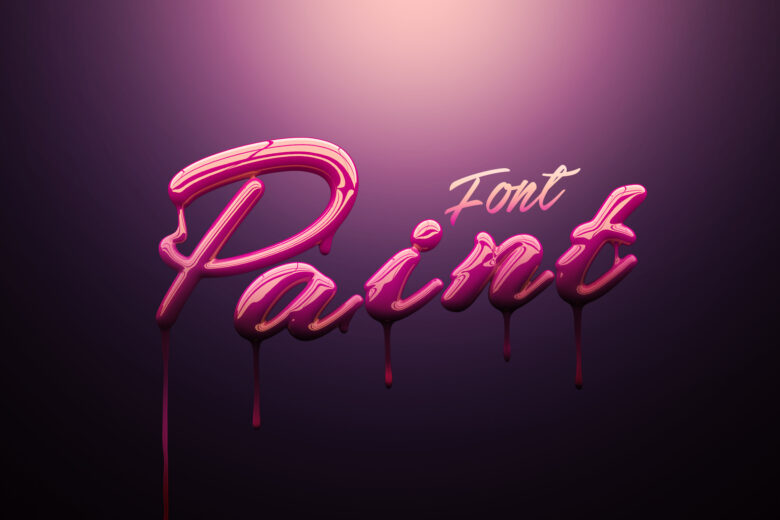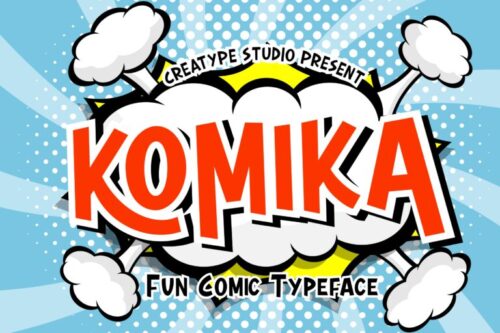
Chọn đúng fonts trong thiết kế Logo
Fonts đóng một phần quan trọng trong việc tạo ra các thiết kế logo thành công, thể hiện bản sắc doanh nghiệp của một chủ thể kinh doanh. Một số mẫu thiết kế logo dựa trên văn bản, trong khi một số khác là các biểu tượng trong hay sự kết hợp của cả hai biểu tượng và kiểu chữ. Trong khâu lựa chọn các phông chữ, phải chú trọng sự liên quan của các phông chữ với các thể loại thiết kế logo được sử dụng.
Cách sử dụng các phông chữ trong một thiết kế logo sẽ tùy thuộc vào các yêu cầu khác nhau. Có thể là một chữ cái hoặc nhiều biểu tượng, ký tự, tùy thuộc vào bản chất kinh doanh của công ty và lĩnh vực hoạt động. Ví dụ,  Công ty FedEx sử dụng một phông chữ có độ chính xác và mạnh mẽ để biểu hiện tầm vóc doanh nghiệp của mình. Nhưng nếu cùng một phông chữ đó được áp dụng cho một doanh nghiệp về lễ hội hoặc một rạp xiếc, nó sẽ không khuếch trương trương tính chất kinh doanh. Do đó, việc sử dụng các phông chữ thích hợp vào đúng thời điểm là yếu tố rất quan trọng với các nhà thiết kế Logo.Sau đây là một số ví dụ minh họa về cách dùng phông chữ với các thể loại Logo khác nhau:Phông chữ cho Logo dạng khái niệm:Logo khái niệm là một thể loại logo mang thông điệp ẩn trong các thiết kế của nó. Ví dụ logo FedEx có chứa hình một mũi tên giữa “E” và “x“. Từ các biểu tượng đã mang một ý nghĩa ẩn trong nó, phông chữ được sử dụng với nó nên được giữ càng đơn giản càng tốt. Một thiết kế phức tạp cần đi kèm với một phông chữ đơn giản như Serif hay San Serif.
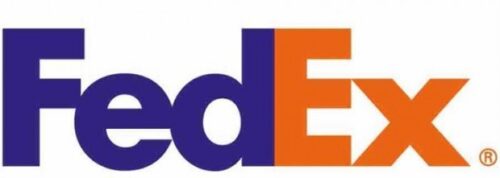
Fonts cho Logo dạng Chữ kýLogo dạng chữ ký rất phổ biến trong ngành công nghiệp thời trang. Nhãn hiệu thời trang chủ yếu sử dụng Logo dạng chữ ký nhằm chuyển tải thương hiệu của mình trên vải. Nhãn hiệu hàng đầu và biểu tượng thiết kế thời trang như Ralph Lauren và được Sherman đã sử dụng phông chữ viết tay cho các thương hiệu thời trang của họ. Sau đây là một số chữ ký hiện đại và các phông chữviết tay có thể được sử dụng cho các nhãn chữ ký và thương hiệu.
Fonts cho Logo đương đại thường dùng cho những xu hướng mới cho ngành công nghiệp thiết kế logo và sử dụng một cái nhìn khá sang trọng và tươi mới. Biểu tượng đương đại bao gồm các đặc điểm của xu hướng thiết kế logo hiện đại, nhằm mục đích tạo sự phân biệt. Hơn nữa, biểu tượng đương đại còn mang ý nghĩa tăng trưởng và thịnh vượng. Dưới đây là một số phông chữ hiện đại mà bạn có thể sử dụng trong thiết kế Logo dạng này.
Fonts cho Logo dạng 3D đang rất thịnh hành. Khái niệm về logo 3D chỉ ra rằng thiết kế nên biểu hiện chủ nghĩa hiện thực và hình ảnh động. Các phông chữ được sử dụng trong Logo 3D bao gồm các phông chữ vuông và phông chữ nổi khối. Dưới đây là một số ví dụ các phông chữ có thể được sử dụng trong các Logo 3D.
Fonts cho Logos mang tính hài hước, vui nhộn (Comic)Tên của thể loại này cho thấy sự hài hước và thể hiện niềm vui trong các loại logo. Logo được tạo cho các lĩnh vực về trẻ em hoặc các công ty giải trí. Vì vậy, phông chữ cho Logo dạng này thường là các nét chữ vụng về, ngộ nghĩnh. Dưới đây là vài ví dụ về phông chữ được sử dụng cho các Logo dạng này.